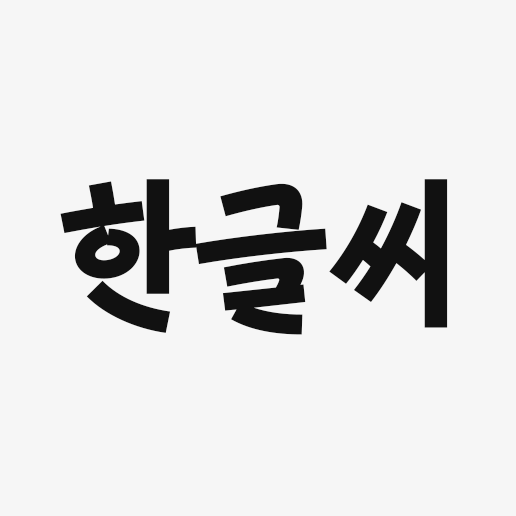
HG시선들
Hangulssi
분류 Sans,민부리
종수 7종
HG시선들은 손글씨의 감성을 모던하게 표현하여 본문에 사용 가능한 산세리프 서체로 재해석했습니다. 손글씨의 특징에서 시작된 서체이지만 본문용으로 사용하기에 무리가 없도록 동일한 자폭으로 느껴지도록 설계하였습니다. 글자의 필순에 따라 자연스럽게 연결되거나 끊어지는 형태와 각 자소의 관계, 그리고 기존의 고딕 서체에서 보기 힘든 "ㄴ, ㄹ"등의 형태적 특징에 의해 새로운 인상을 가진 서체로 디자인하였습니다.
7가지 웨이트의 풍부한 패밀리로 구성되어 있어 용도에 맞게 사용할 수 있으며, 2,350자의 한글 글립이 디자인되어 있습니다. 각 두께의 한글 글립들은 동일한 폭으로 이루어져 있어 Grid에 맞춰서 쉽게 활용할 수 있습니다. 영문과 숫자 디자인은 한글 글립들의 손글씨적 특징인 속도감과 형태를 적용하여 디자인하였고 모던한 산세리프적인 마감 처리를 그대로 가져왔습니다.
• 김동관